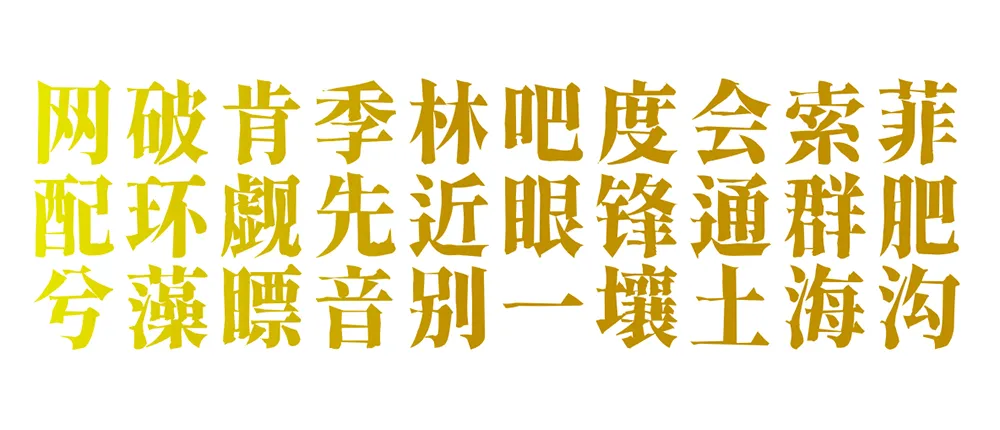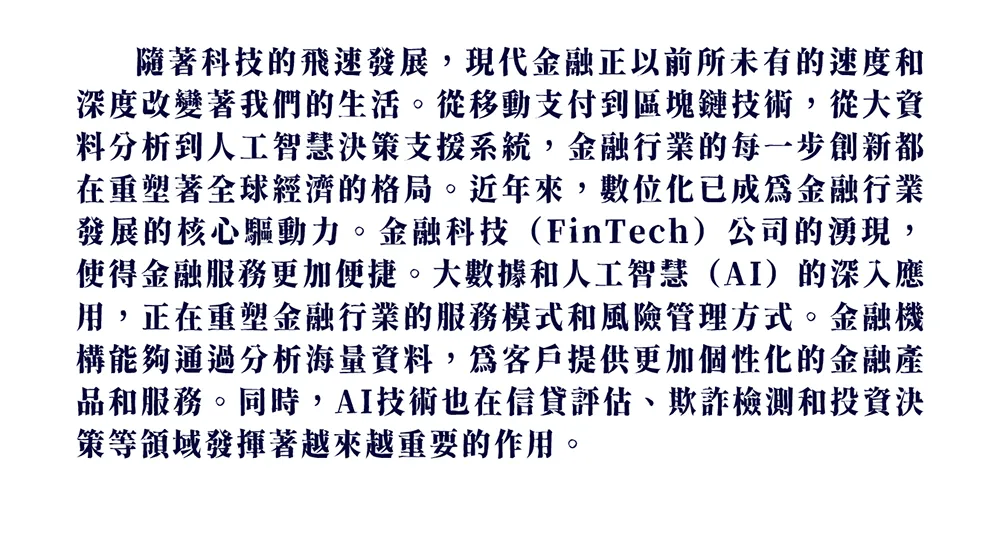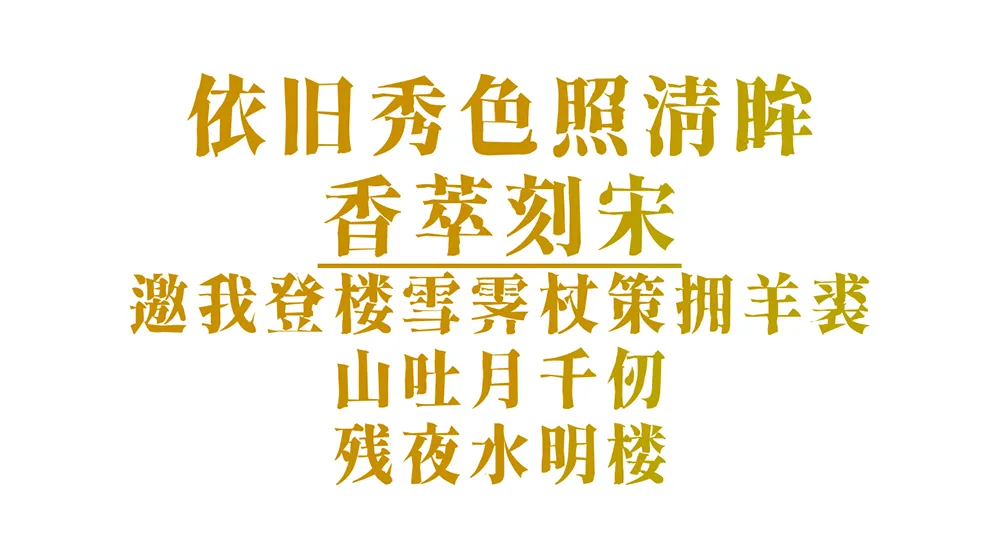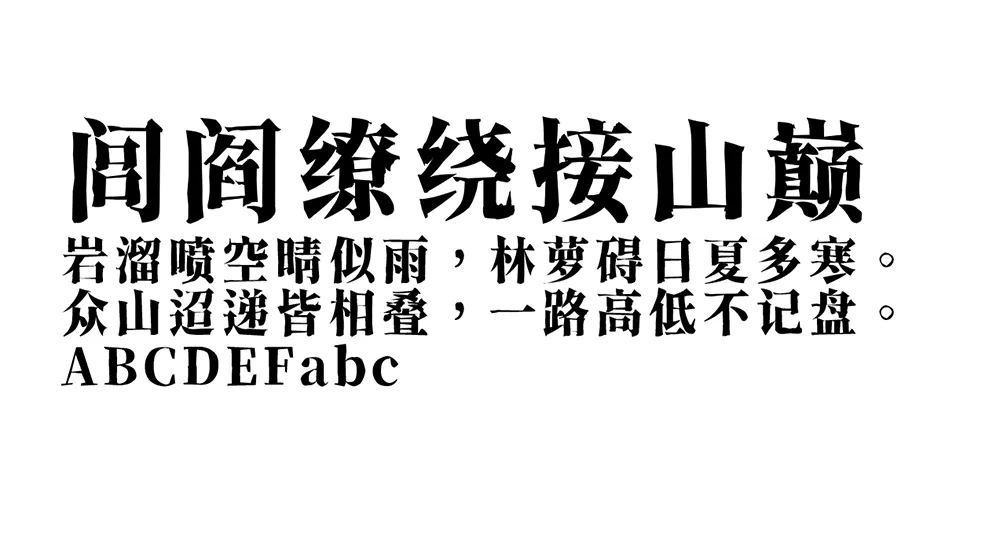
香萃刻宋預覽
香萃刻宋介紹
“香萃刻宋”(Xiangcui Kesong)是一款基於思源系列開源字體改造而成的中文字體,支持簡繁漢字,允許個人或企業免費商用。“香萃扁刻宋”(Xiangcui Bian Kesong)為其衍生作品。
這款字體有意模仿了雕刻宋體的外觀特點,通過仿古的處理,達到兼具端莊和典雅的特徵。字體筆畫尖銳,特色明顯,視覺吸引力強,適合各類設計與印刷,有濃烈的視覺增強效果。字體普遍使用舊字形,同時適用於標題和正文。用作標題時,筆畫的粗糙感強,特點明顯,富有文學感與人文氣息。